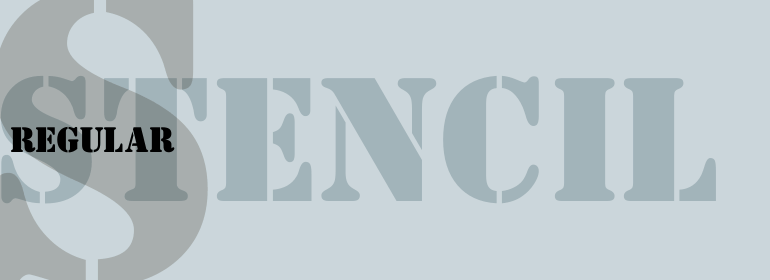
Stencil
Stencil,这款字体结构工整、笔画清晰,兼顾美观与易读性,适用于标题、正文、海报、包装、LOGO 等多种场景。字形优雅稳定,风格百搭耐看,适配日常排版与创意设计,让文字呈现更舒适、更具质感。Stencil一笔一画,皆是细节,以均衡的比例、流畅的线条打造舒适视觉体验,字形端正大气,风格简约现代。无论是商业设计、品牌宣传还是日常排版,都能轻松驾驭,让文字更有格调与力量。Stencil字体下载。
字体品牌: Bitstream(Monotype) 设计师:Powell,Gerry 字体分类:衬线体 字体属性:外文 字符集:Unicode 发布时间: 2018